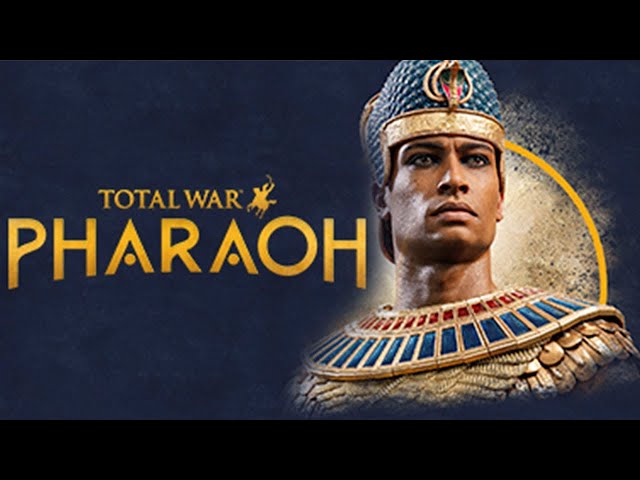
Шрифт в Total War: Pharaoh (карта, описание, и т.д.)
Шрифт создан в стиле ар-деко (1920-1940 гг. ХХ века)
Основной шрифт игры Total War: Pharaoh
Основной шрифт (на карте, в заголовках, и т.д.), используемый в игре Total War: Pharaoh, называется Mendl Sans Dusk. Это шрифт в стиле ар-деко, автором которого является Анджел(а) Квонг, а правообладателем - английская компания Dalton Maag Ltd. Данный шрифт создан в период 2020-2021 годов, не поддерживает кириллицу, не имеет свободной лицензии (только временную бесплатную версию) и стоит 42$ (вместе с похожим шрифтом Mendl Sans Dawn).
Существует схожий шрифт с Mendl Sans Dusk под названием Transat, который отличается лишь нижней петелькой в заглавных буквах R и Р. Его создатель дизайнер Грег Шаттерс, правообладателем является американская компания Typetanic Fonts. Данный шрифт описывается как геометрический шрифт без засечек, созданный под впечатлением вывесок в стиле «ар-деко» на терминале океанских лайнеров в Гавре (Франция) в 1930-х годах.
Кириллическая версия шрифта Mendl Sans Dusk
для создания русификатора к игре Total War: Pharaoh
Описание кириллической версии шрифта
Кириллический алфавит вшит (добавлен) в оригинальные файлы шрифта Mendl Sans Dusk, доступно три языка (русский, украинский и белорусский), четыре вида шрифта (Regular/обычный, Medium/средний, SemiBold/полужирный, Bold/жирный).
Оригинальный латинский шрифт имеет в себе как заглавные буквы, так и строчные, но в игре используются только заглавные буквы (для текстов с использованием строчных букв используется шрифт Noto Sans). Поэтому, чтобы локализаторам было легче работать, я добавил заглавные буквы как в линейку заглавных букв, так и в линейку строчных букв. То есть при печати в локализации любых кириллических букв всегда будут печататься только заглавные.
Русифицировать этот шрифт не проблема. Например, буквы А, В, Е, Ё, К, М, Н, О, Р, С, Т, У, Х уже есть, их можно из латиницы взять. Буквы Б, Г, Ж, И, Й, Ф, Ъ, Ы, Ь, Ю, Я, Э будет легко сделать на основе латиницы. А вот над буквами Д, З, Л, П, Ц, Ч, Ш, Щ надо будет подумать, чтобы они вписывались в общую концепцию шрифта. При чём, это только заглавные буквы шрифта. Прописные из этого шрифта, вроде бы, не используются в игре. Там какой-то простой рубленный шрифт, похож на стандартный, без наворотов. 3десь надо с Троей сравнивать, там тоже в заголовках буквы стилизованные под греческий шрифт, а более мелкие надписи-описания, обычные рубленные прописные, вроде бы. Скорее вопрос как русифицированный шрифт закинуть в игру, чтобы она именно его воспринимала. пробовал закидывать русификатор, у него не получилось, но тут понятно, так как кириллицы нет (или моды пресс-версия не поддерживает), а вот что было со строчным рубленным шрифтом он не написал.
А вот над буквами Д, З, Л, П, Ц, Ч, Ш, Щ надо будет подумать, чтобы они вписывались в общую концепцию шрифта.